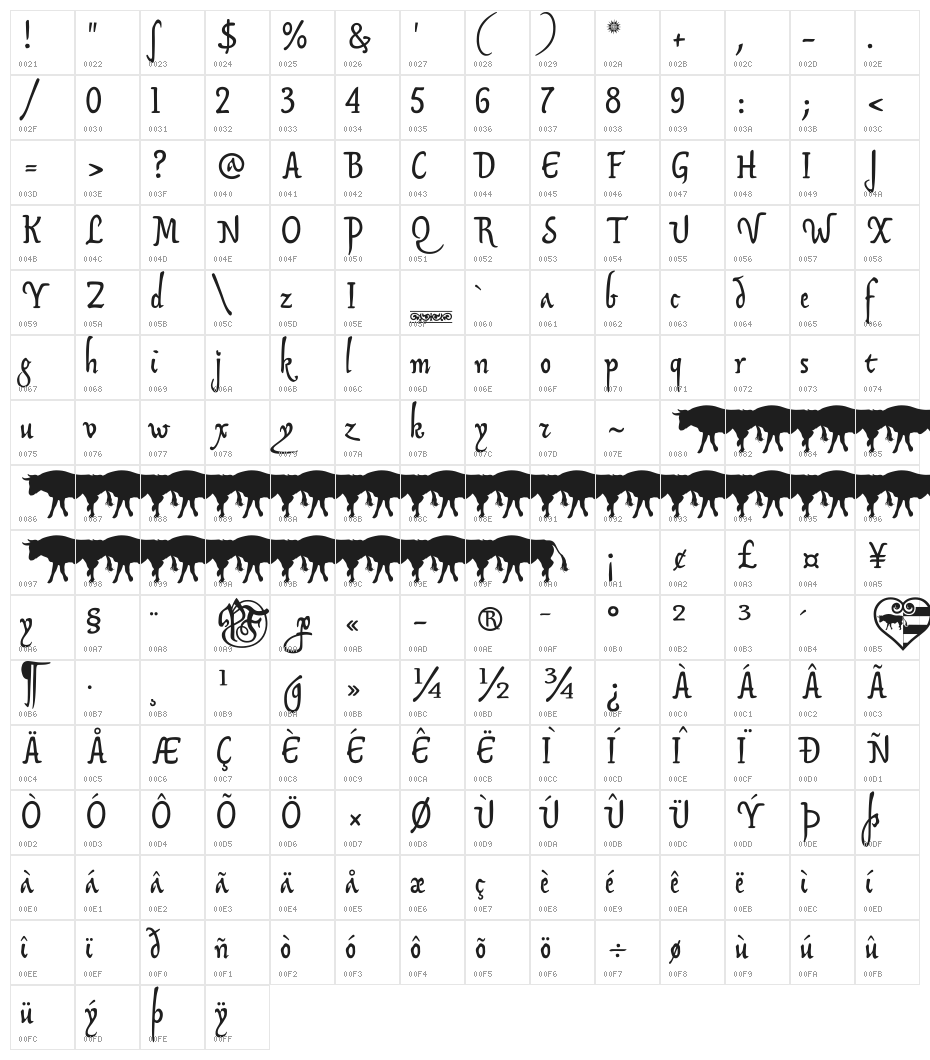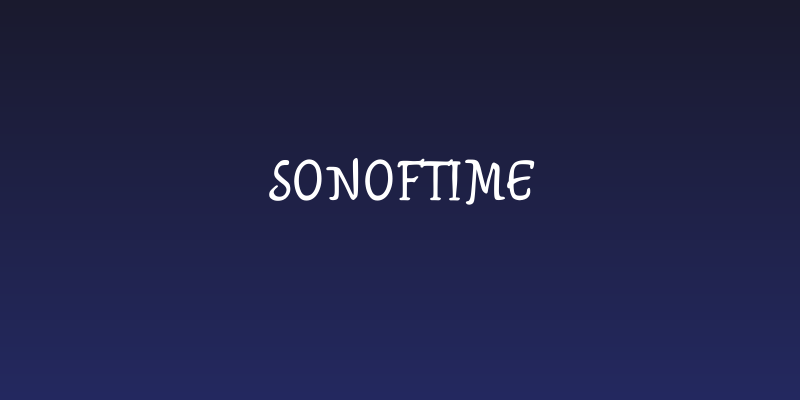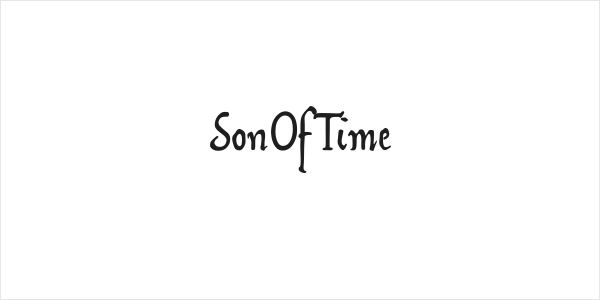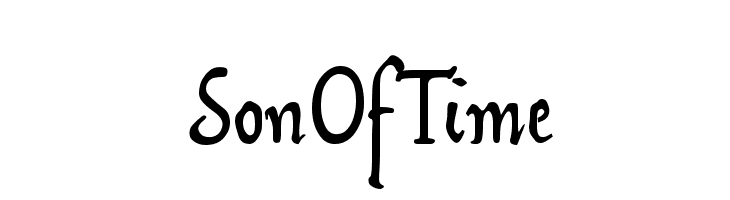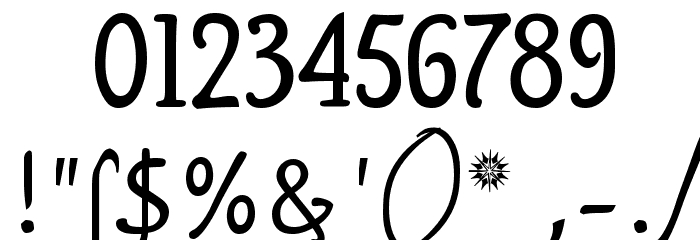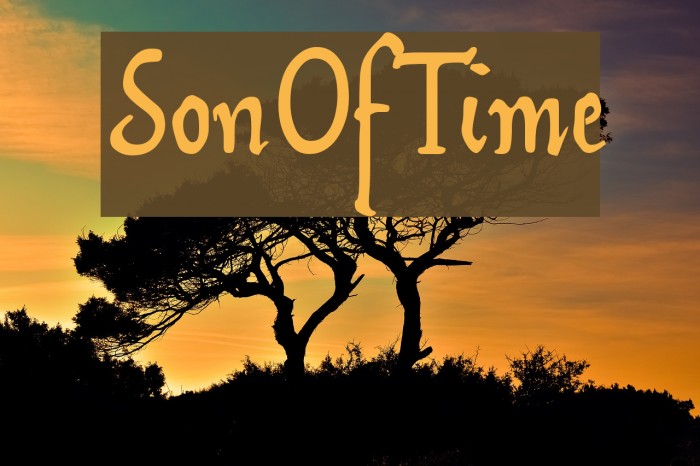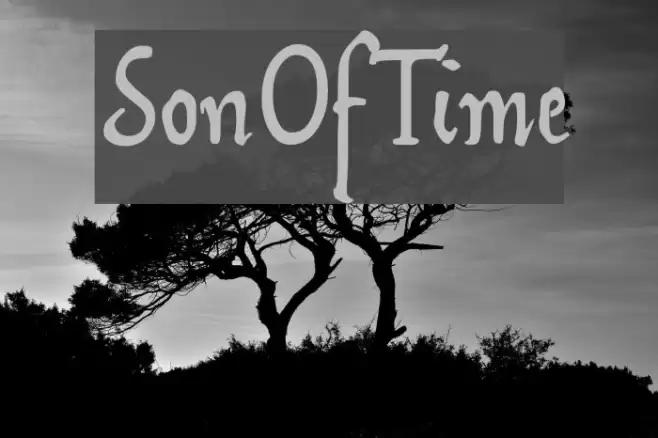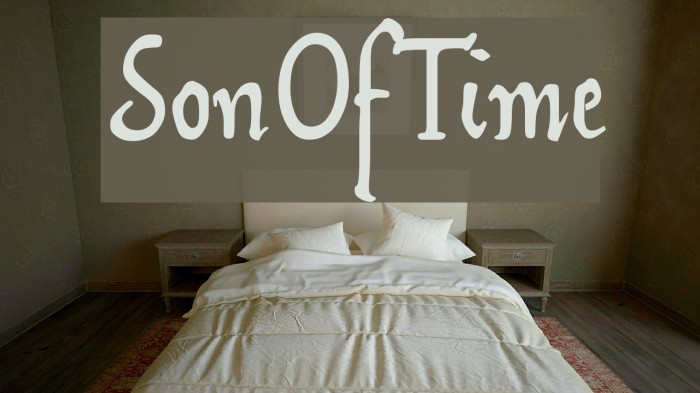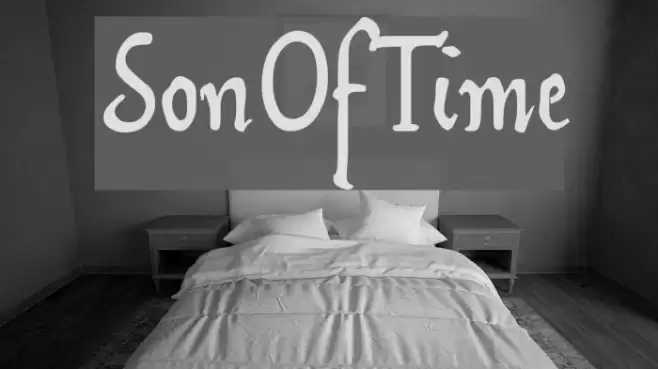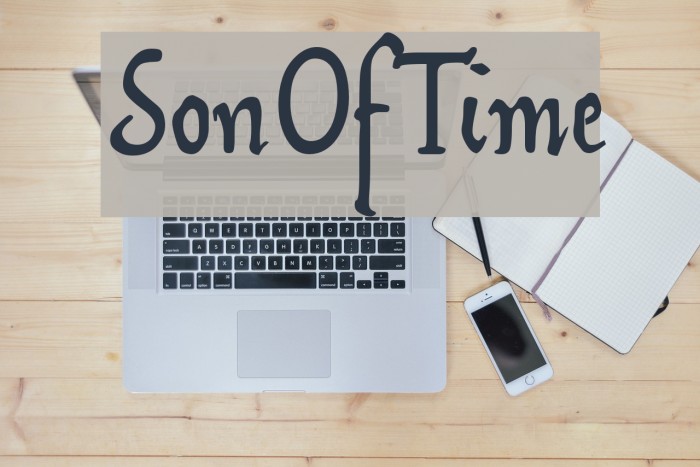
SonOfTime Font
✎ Calligraphic
| Categorie | Calligraphic |
| Caso d'uso | Logos, Posters, Invitations |
| Progetti proposti | Ideal for creative projects such as invitations, greeting cards, posters, and branding materials that require a touch of artistic flair. |